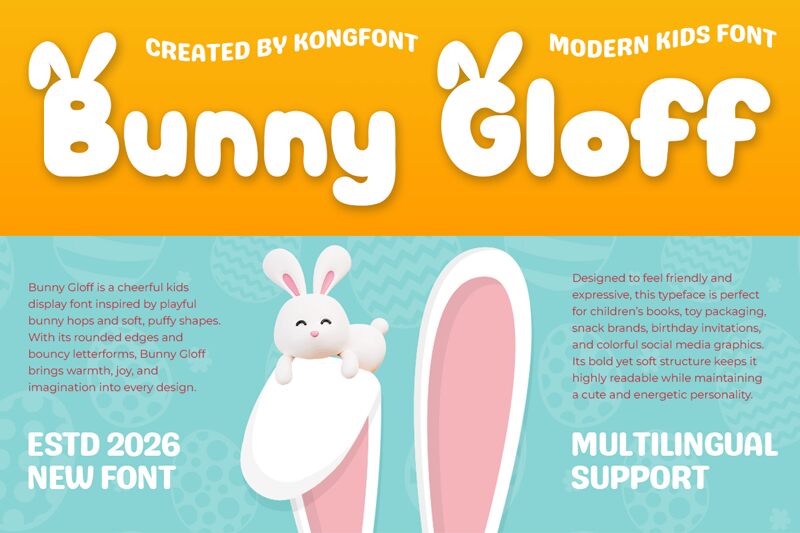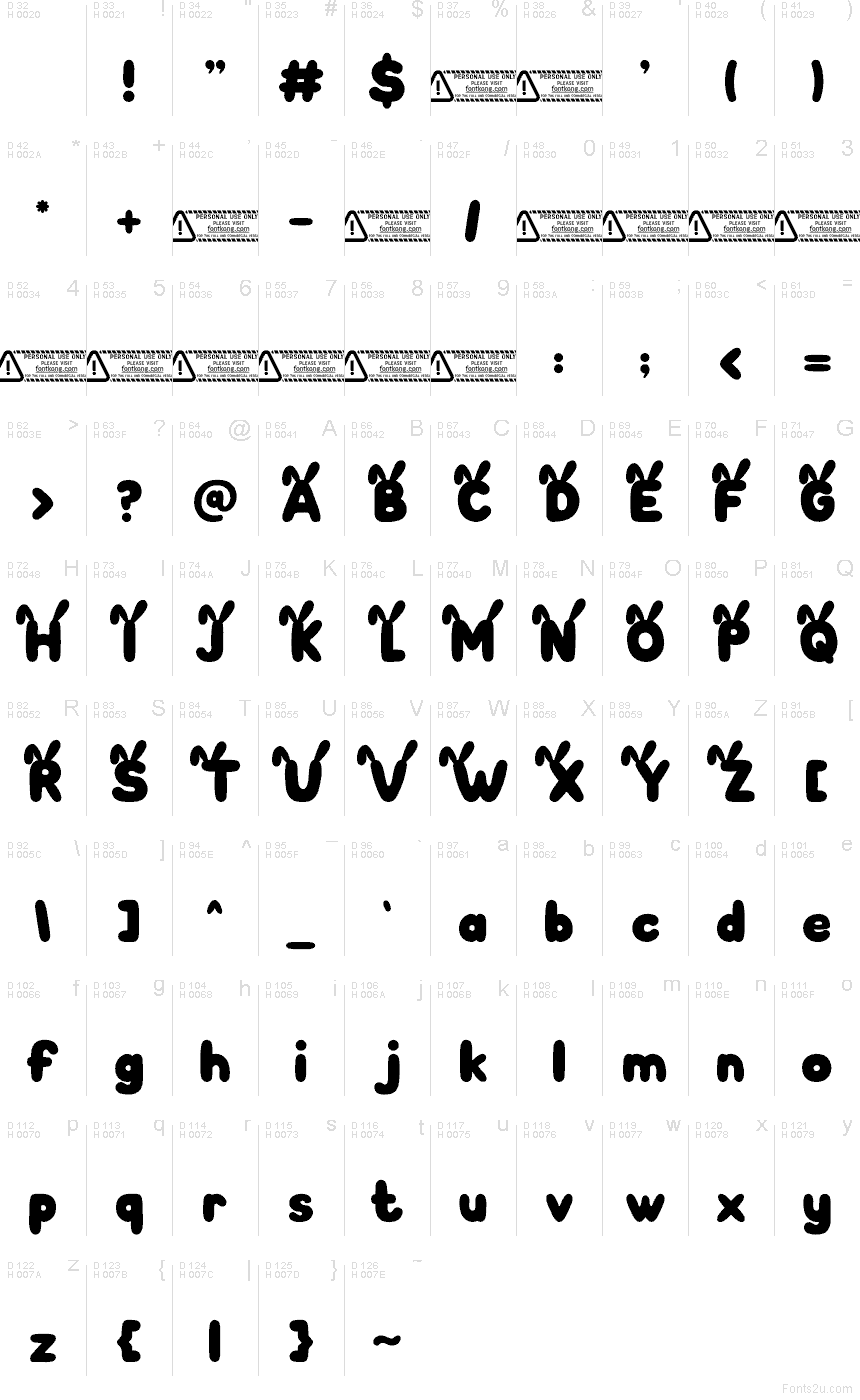
Kong Font 设计的 Bunny Gloff 是一款免费的复活节展示字体,其特色在于柔软蓬松的造型和清晰的兔子图案。圆润的字形让整体设计显得友好且简洁,而字形中模仿兔耳朵的开口设计,使这套字体与复活节和春天的氛围完美融合,完全不同于那些普通通用的泡泡字体。
这款字体非常适合用于复活节传单、寻蛋活动标识、儿童派对邀请函、季节性包装以及春季社交媒体海报。其饱满的轮廓能让短语呈现出明快生动的视觉效果,且自带的兔子元素无需额外配图,即可为礼品标签或促销标题增色不少。